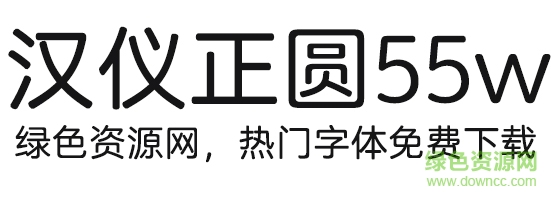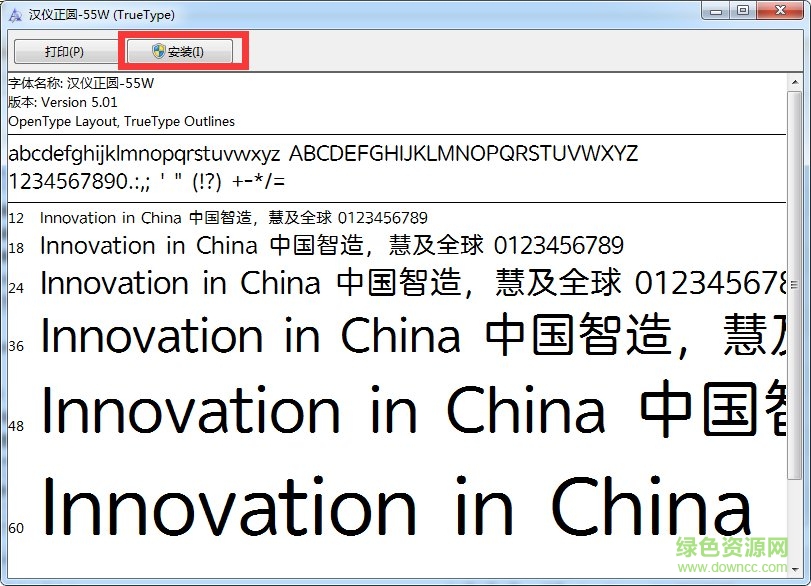
漢儀正圓55wttf是一個(gè)外觀圓潤(rùn)的字體。使用本字體可以設(shè)計(jì)商業(yè)標(biāo)識(shí),進(jìn)行平面排版設(shè)計(jì)、廣告設(shè)計(jì)等等。使用的場(chǎng)景非常多。字體文件可以在photoshop和word等應(yīng)用程序中打開使用!喜歡這款字體的用戶快來拿走吧。
字體風(fēng)格:國(guó)際化/簡(jiǎn)約/時(shí)尚/現(xiàn)代/男性/女性/溫柔/穩(wěn)重/休閑/優(yōu)雅
推薦場(chǎng)景:標(biāo)志/導(dǎo)視/廣告/正文/屏顯/書籍/影視/游戲